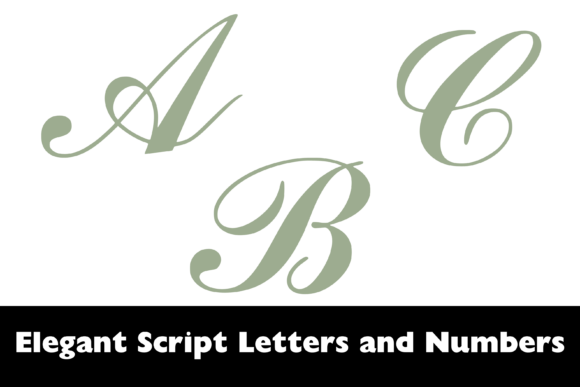
Green Script Alphabet Letters Numbers
Пошук відповідних елементів дизайну може бути складним, але Green Script Alphabet Letters Numbers пропонує виняткову колекцію, яка миттєво покращить вашу роботу.
Створений з високою точністю, Green Script Alphabet Letters Numbers забезпечує чисті вектори, плавну типографіку та комерційну ліцензію для вашого спокою.
Незалежно від того, чи створюєте ви продукти POD (друк на вимогу), весільні запрошення або графіку для соціальних мереж, Green Script Alphabet Letters Numbers стане ідеальним вибором.